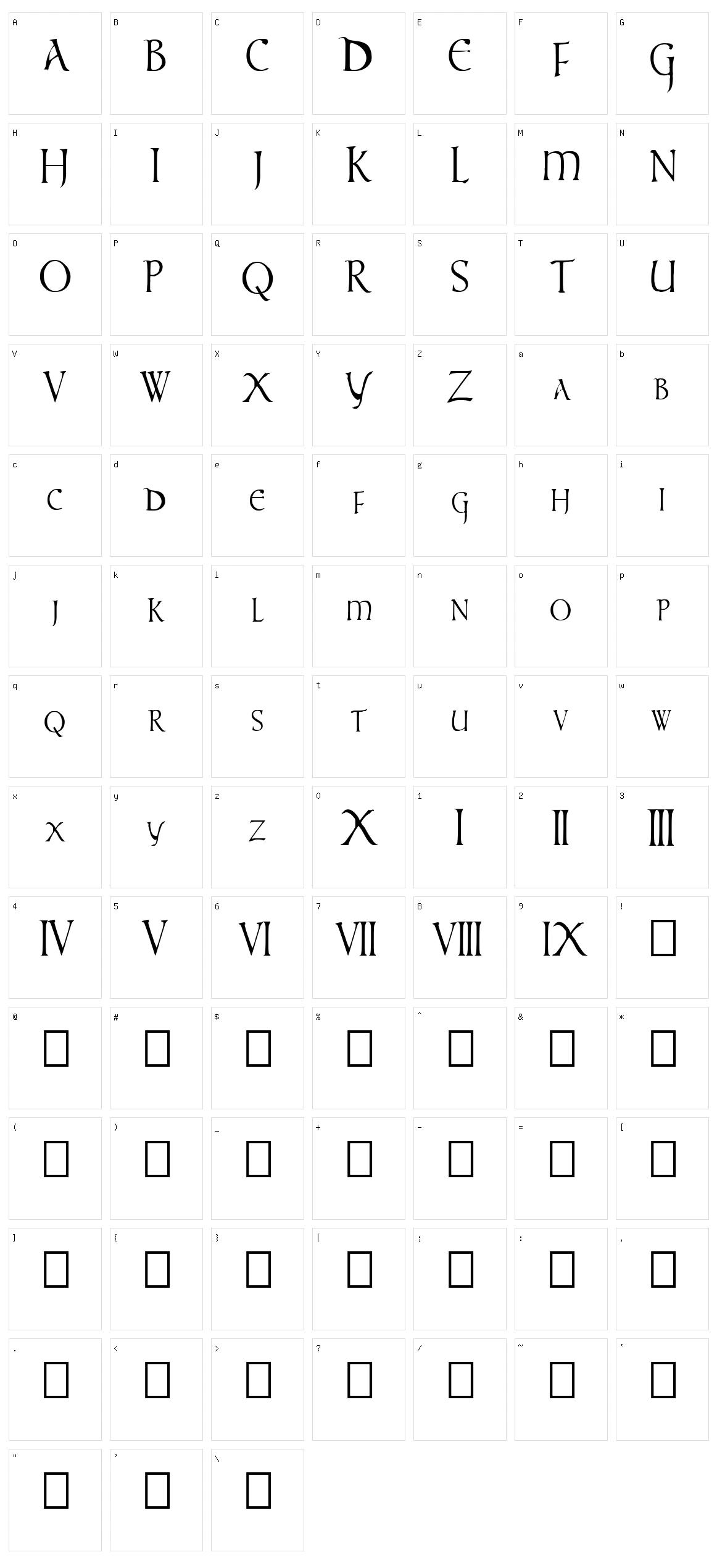
TIMES NEW VESPASIAN
fonte inspirada nas capitais rusticas romanas quando de sua transicao para as unciais
TIMES NEW VESPASIAN
typeface inspired in the roman capitals initials when the uncial style has begin, transformating their forms